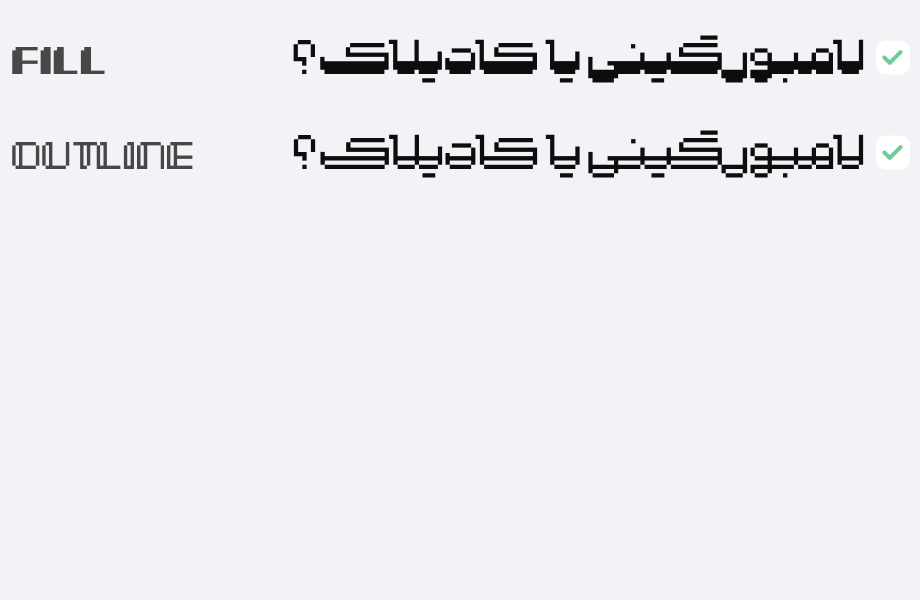
ایده ی فونت رادیو در حین انجام یک بازی قدیمی پیکسلی در ذهنم جرقه زد و بعد از بررسی ضخامت قلم در دنیای دیجیتال شروع به طراحی کردم. هدف من طراحی یک تایپ فیس نمایشی با دو سبک Fill و Outline بود که برای استفاده دیجیتال ایده آل باشد.
سبک Fill، ضخامت مورد نیاز و انتظارات شما را از یک فونت نمایشی برطرف می کند.
سبک Outline ، پس از بررسی ساختار اسکریپت و اتصالات حروف طراحی شد، و شما میتوانید از این دو سبک به عنوان مکملی برای یکدیگر استفاده کنید و دیزاین های خود را خلاقانه تر دیزاین کنید.
فونت رادیو، برای تیترهای جسورانه و متون مختصر ایده آل است.
در نظر گرفتن اعراب گذاری متناسب